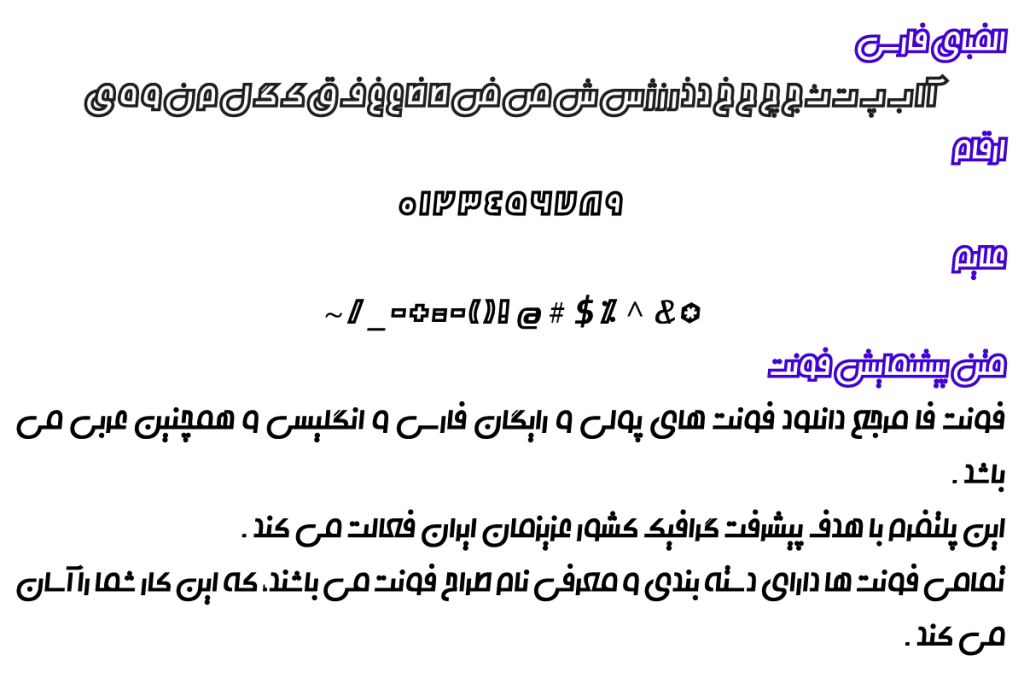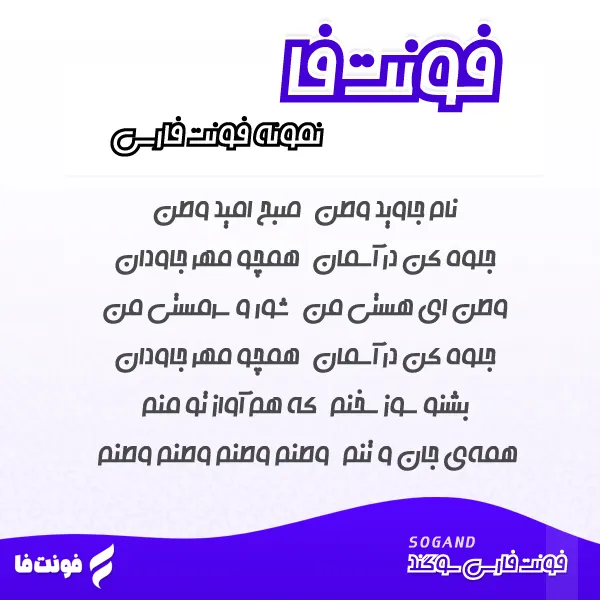
فونت فارسی سوگند – SOGAND
طراح فونت: حسین تقی زاده نوع فونت: فونت عنوان و فونت هندسی
پیشنمایش فونت سوگند
توضیحات و معرفی فونت سوگند
فونت فارسی سوگند ( SOGAND ) از مجموعه فونت های آزاد می باشد، همچنین نوع فونت عنوان و هندسی می باشد.
فونت فوق العاده زیبای معرفی شده توسط حسین تقی زاده طراحی و ساخته شده است.
نسخه بهبود یافته همین تایپ فیس با نام Dima sogand New Font در بسته دریافت موجود می باشد.
همچنین فونت SOGAND در 2 وزن معمولی و توخالی خطی است.
در لیست زیر می توانید وزن های این فونت فوق العاده زیبا را ببینید.
- SOGAND Regular
- SOGAND Outline
در تصویر زیر میتوانید شعر دلنشین «نام جاوید وطن» را ببینید که با این تایپ فیس فارسی طراحی شده است.